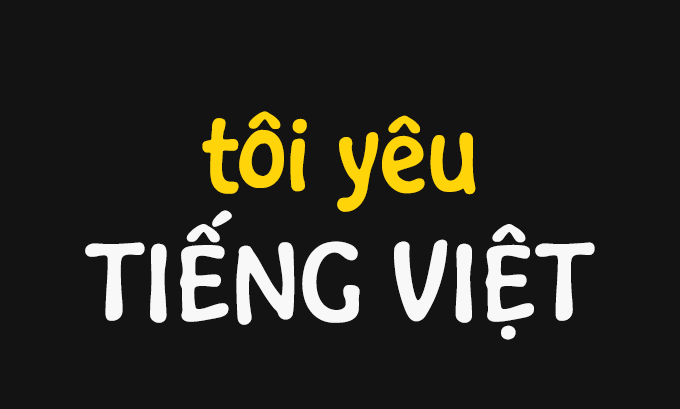
Font SVN Saycheez Việt Hóa
Font SVN Saycheez là một phông chữ vui nhộn, đáng yêu thuộc bộ font SVN, font chữ mang đến phong cách ngộ nghĩnh và trẻ trung cho các dự án thiết kế. Với những đường nét mềm mại và dễ thương, font SVN Saycheez đặc biệt phù hợp cho các thiết kế dành cho trẻ em, quảng cáo sản phẩm sáng tạo, hay các ấn phẩm truyền thông mang tính giải trí. Font này giúp tạo ra không khí vui tươi, thân thiện và dễ dàng thu hút sự chú ý của người xem. Nếu bạn đang tìm kiếm một phông chữ độc đáo để tạo điểm nhấn cho dự án, font SVN Saycheez chắc chắn sẽ là sự lựa chọn lý tưởng.